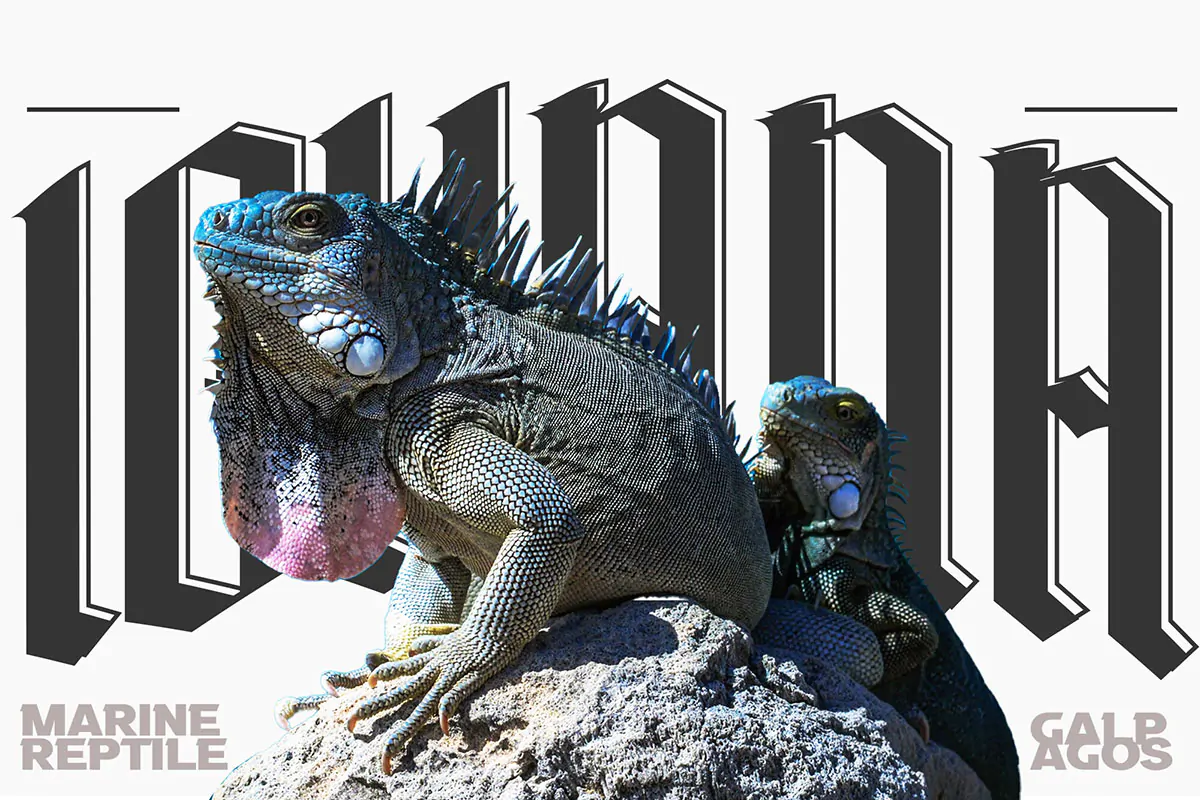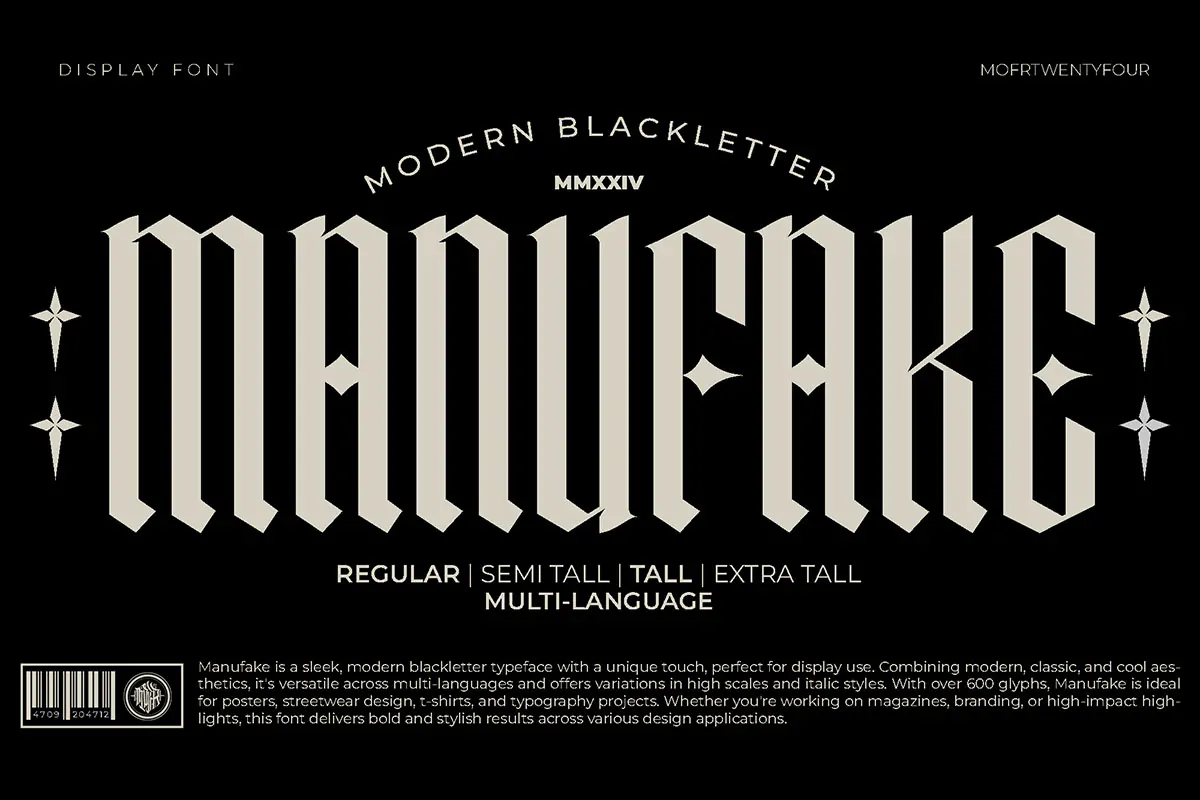
فونت کلاسیک Manufake
فونت کلاسیک انگلیسی
فونت کلاسیک Manufake یک قلم فوق العاده زیبای انگلیسی است که مناسب برای طراحی روی بسته بندی محصولات، ظروف یکبار مصرف، طراحی پوستر، تتو و … میباشد.